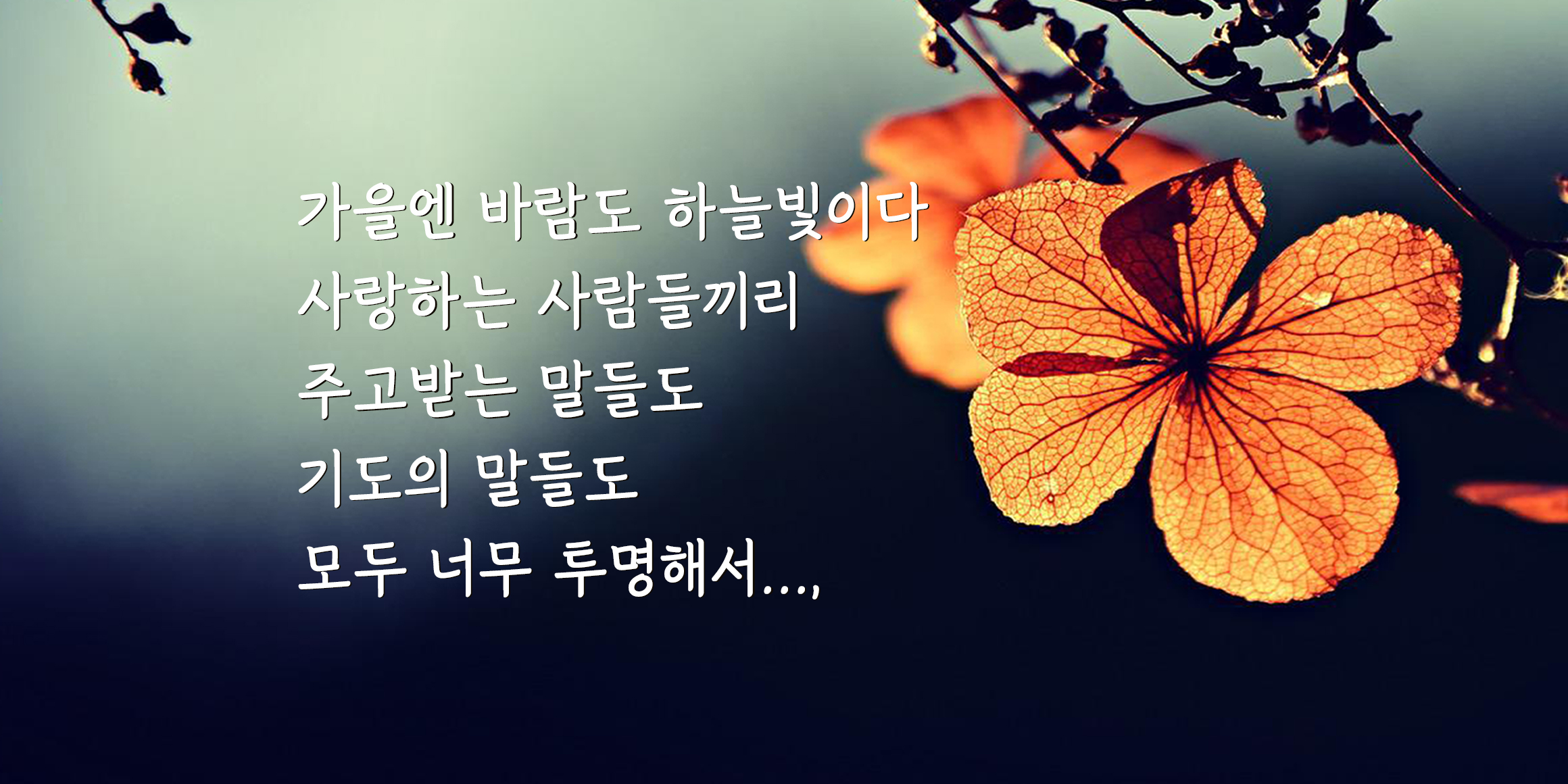
DX가을동화
서정적이고 잘 정돈된 단아한 느낌의 폰트입니다. 크고 작은 자형의 구조 대비가 안정적이고 예쁘며, 손으로 쓴 듯한 글줄의 흐름에서는 손글씨의 감성을 느끼게 하여 본문, 제목용으로 사용하기에 적합한 폰트입니다.
• DX가을동화 / DXautumnfairytale